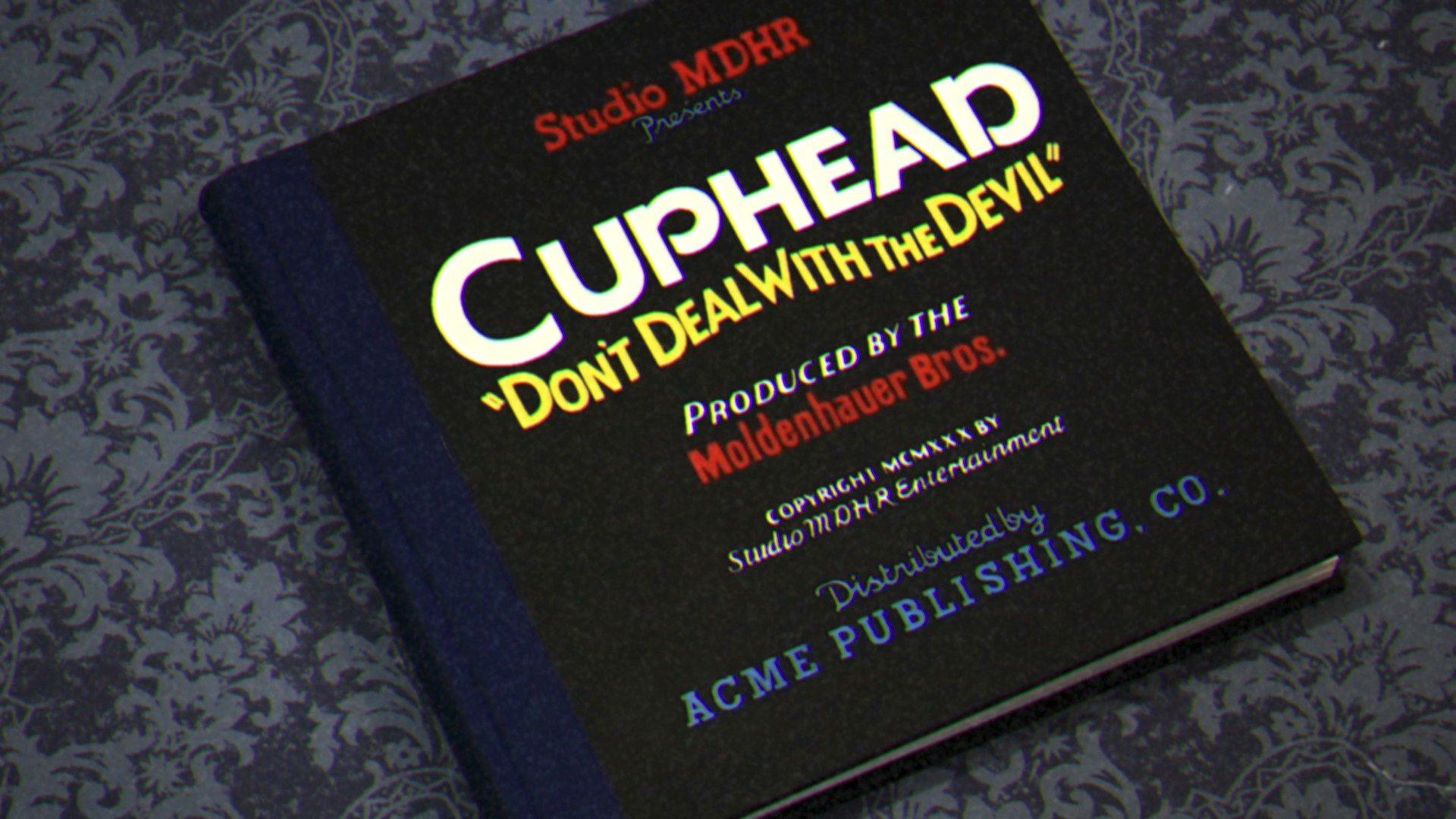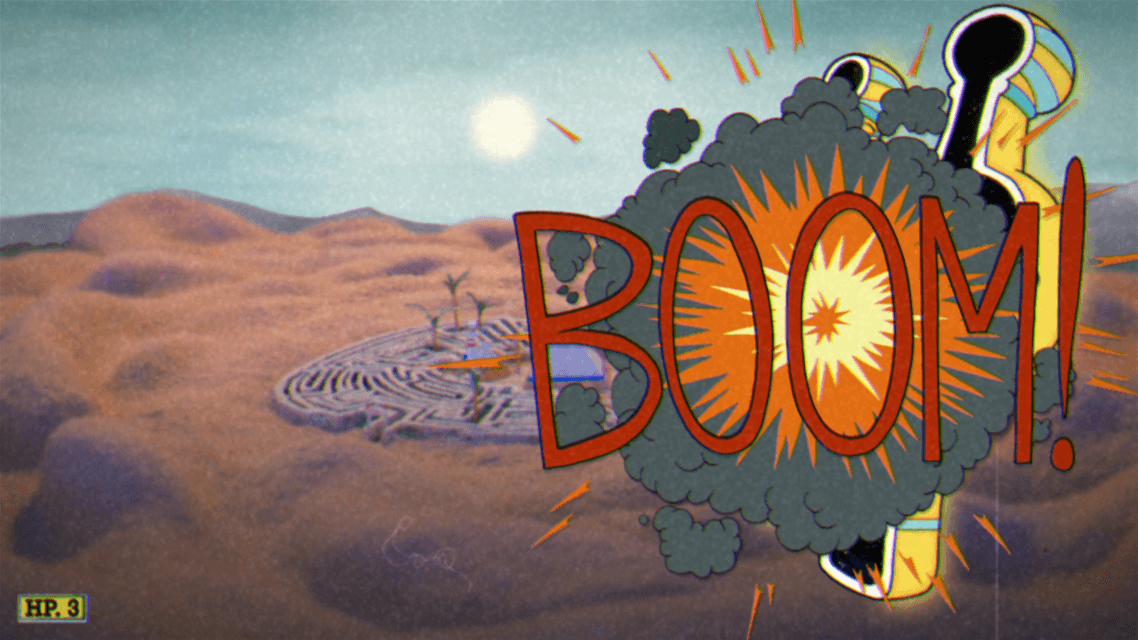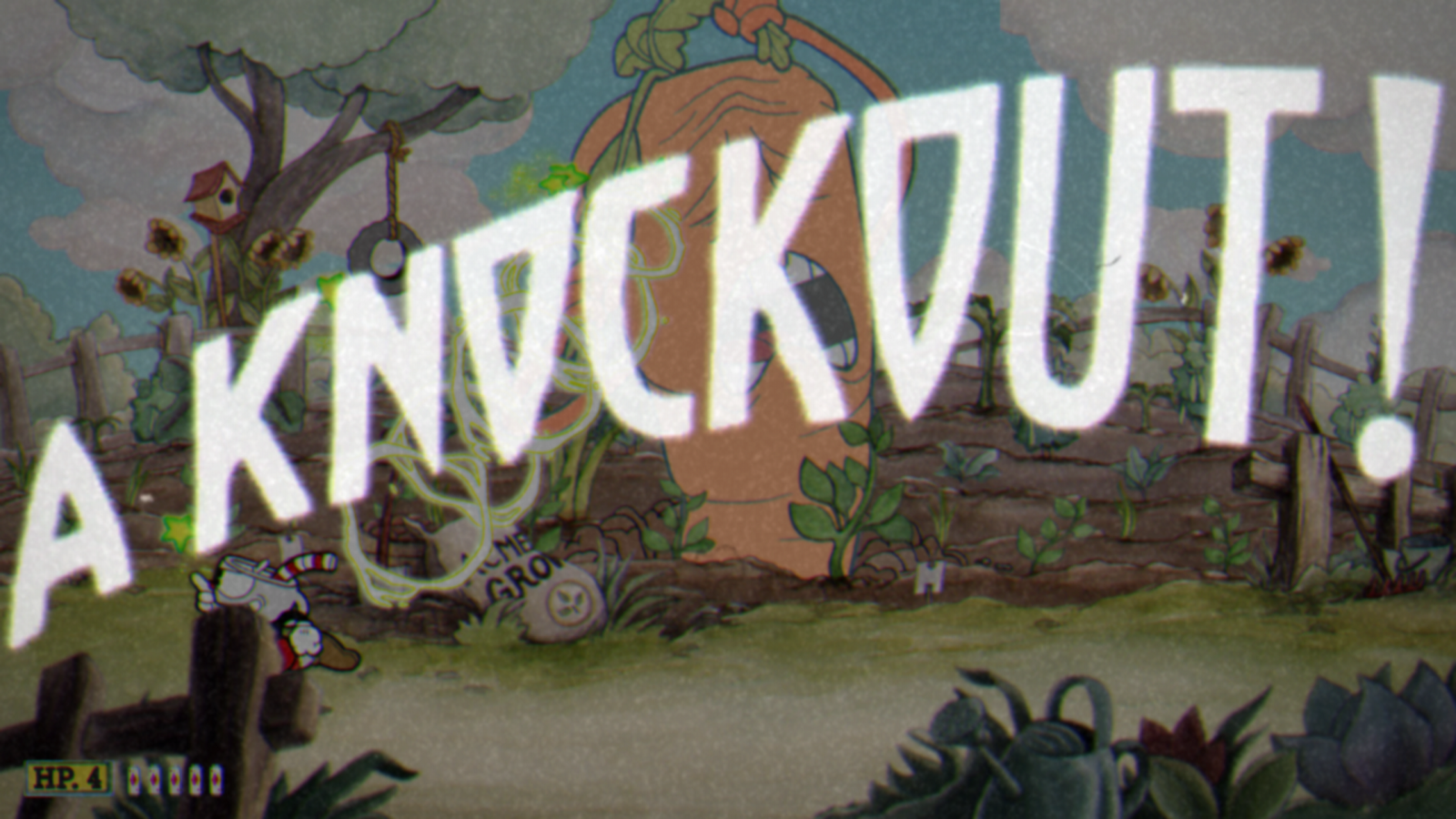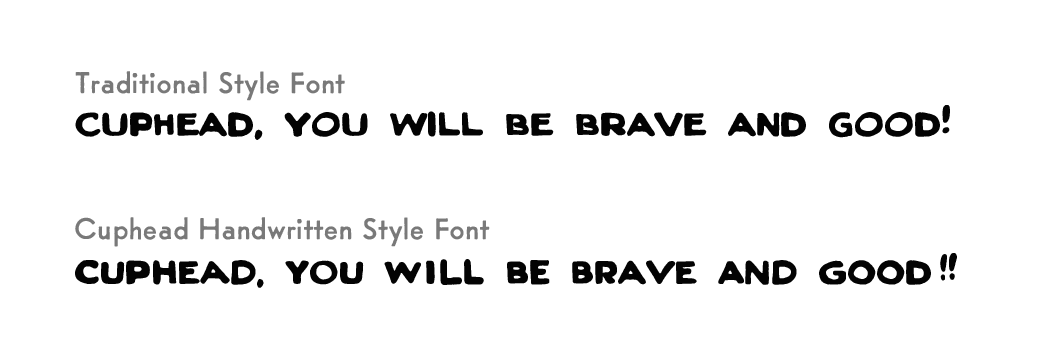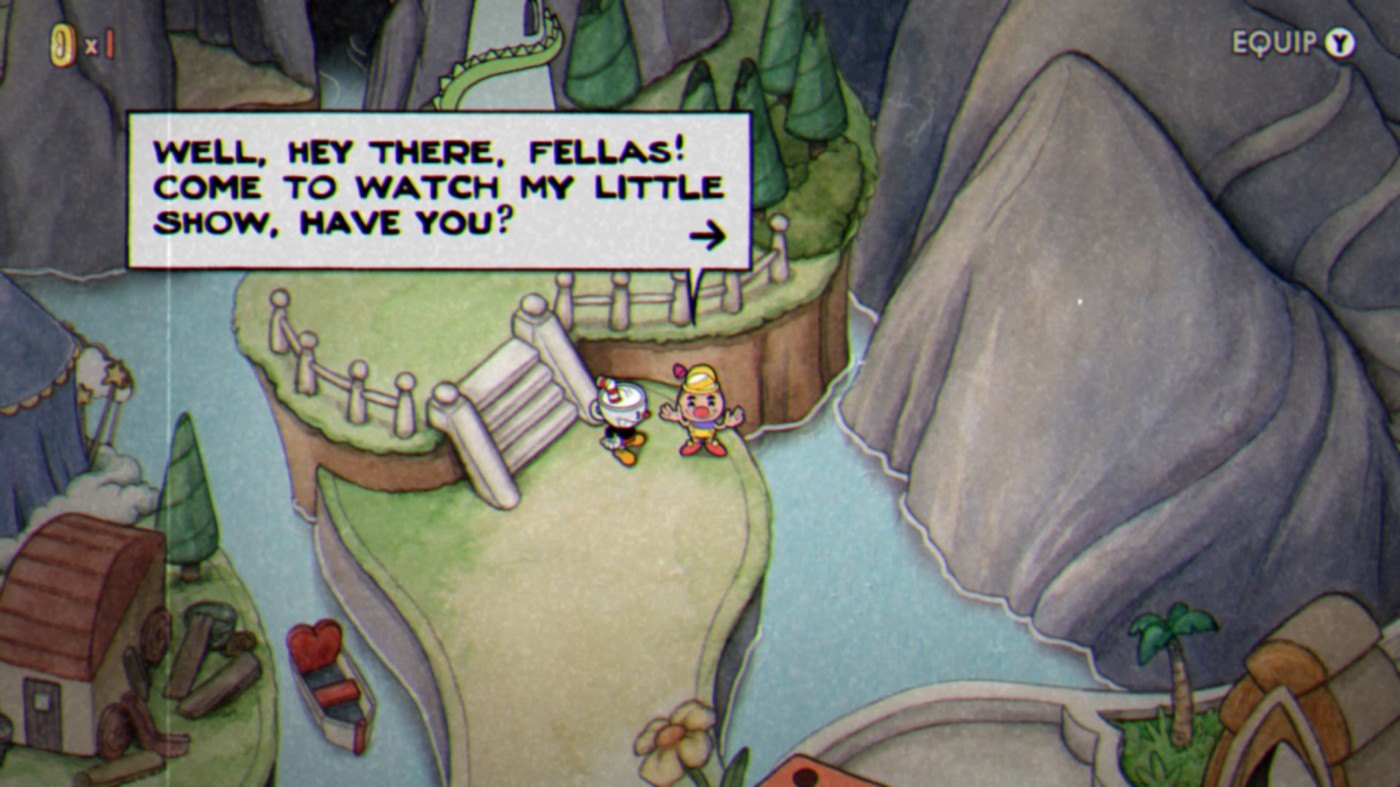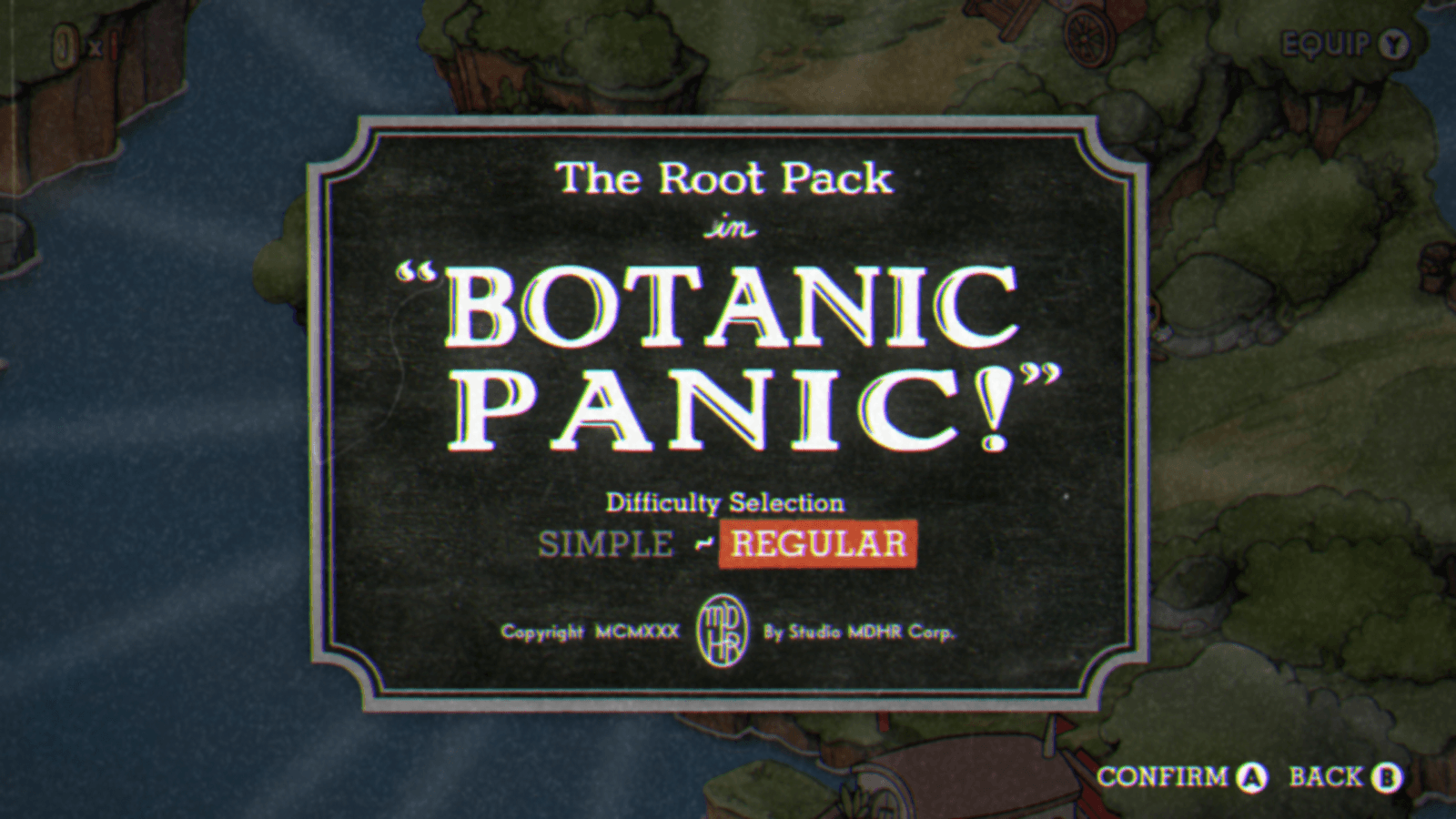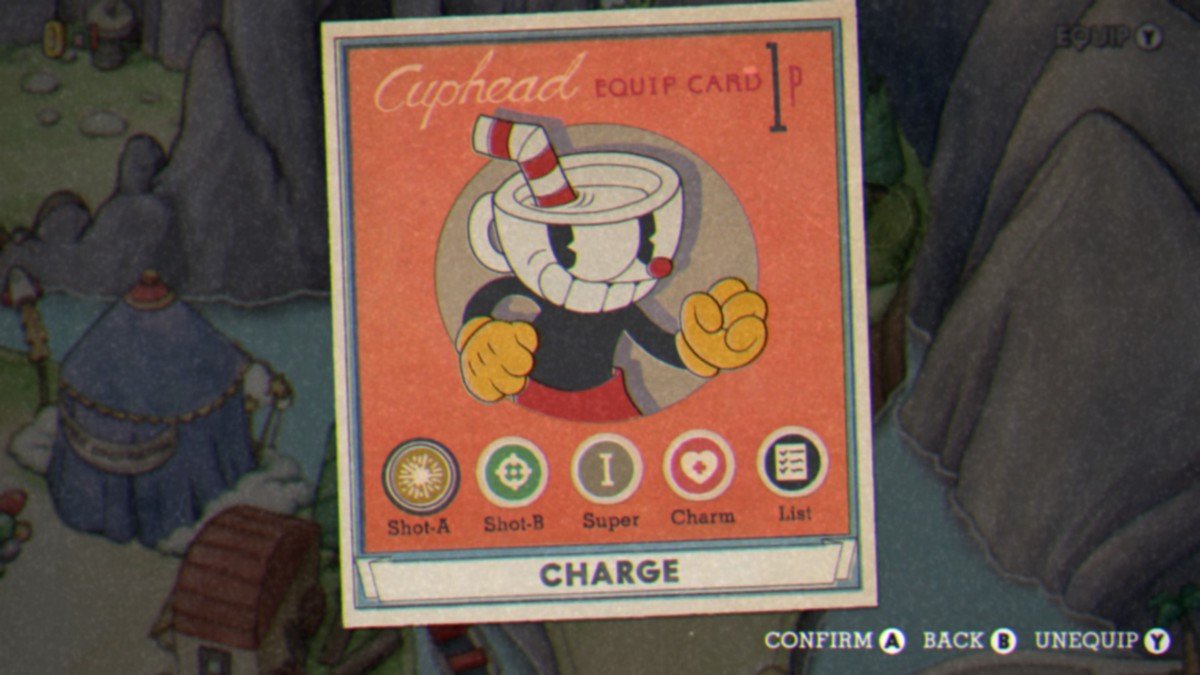
A tipografia em “Cuphead”
Jogo lançado no segundo semestre de 2017 impressiona pela direção de arte cuidadosa e trabalho tipográfico
Os fãs de jogos de plataforma ganharam um motivo para comemorar o mês de setembro de 2017: depois de ser adiado várias vezes, foi lançado “Cuphead” (disponível para PC e Xbox One), primeiro trabalho do estúdio MDHR. O jogo — que já era muito aguardado há anos — não decepcionou. Foi considerado um dos jogos do ano, sendo, por exemplo, premiado pelo The Game Awards como Melhor jogo independente de estréia; Melhor Jogo Independente e Melhor Direção de Arte.
Mas não só quem é fã de games de plataforma aproveitou “Cuphead”: o lançamento foi um presente também para fãs de desenhos animados. E, para o olhar mais atento, também para os interessado por tipografia. O jogo — que narra a saga dos irmãos Cuphead e Mugman enquanto tentam não perder suas almas para o diabo — é inspirado na estética das animações dos anos 1930 e 1940. Por isso, parte importante da sua direção de arte passa por aplicar essa estética ao desenho das letras que acompanham seus cenários e personagens.
[quoteesquerda]Quase tudo foi desenhado exclusivamente para “Cuphead”. Apenas uma fonte foi comprada externamente[/quoteesquerda]
“Cuphead” utiliza a tipografia como importante elemento narrativo (não apenas comunicativo) em momentos chave do jogo. Qualquer pessoa que tenha jogado “Cuphead” deve concordar: a aparição das frases “A KNOCKOUT!” ou “BRAVO!!!” preenchendo quase toda a tela nos finais de fase gera uma sensação de recompensa à altura da alta dificuldade de vencer cada etapa do jogo. A tipografia ainda ajuda a estabelecer o ambiente de cada fase: as batalhas com “chefões” são iniciadas com a frase “WALLOP!” escrita toda em letras maiúsculas, enquanto que as fases de plataforma (sem chefes) iniciam com “Run’n Gun!” escrita com maiúsculas e minúsculas e em tamanho menor na tela, de forma menos “urgente”. As letras ainda aparecem como elemento narrativo na forma de onomatopéias, no decorrer de algumas fases do jogo.
A preocupação do estúdio com esse elemento está não apenas no uso, mas também nos desenhos das letras. Quase tudo foi desenhado exclusivamente para “Cuphead”. Apenas uma fonte foi comprada externamente. A Silentina, baseada em intertítulos de filmes do cinema mudo. Para realização deste trabalho tipográfico fizeram parte da equipe do estúdio dois profissionais especializados: Warren Clark — responsável pelas peças de lettering — e Mark Simonson, que atuou como consultor em tipografia e também desenvolveu seis das fontes utilizadas.
[quotedireita]As fontes do jogo foram produzidas a partir de amostras escaneadas de tipografias da década de 1930 e tracejadas digitalmente[/quotedireita]
É importante esclarecer que tecnicamente lettering não é a mesma coisa que tipografia: o primeiro refere-se ao desenho de letras pensadas para uma composição específica; já a tipografia diz respeito à sistematização do caracteres desenhados, com o objetivo de serem aplicados a qualquer layout. Entretanto, convenciona-se abranger o lettering dentro do escopo do termo “tipografia”.
“Cuphead” se utiliza dos dois recursos. Por exemplo, o título da imagem acima — “A KNOCKOUT!” é um lettering — , onde cada caractere foi pensado especificamente para a composição deste título, no qual a palavra é composta por uma curva crescente da esquerda para a direita (note como as duas letras “K” são diferentes uma da outra nesse contexto). Já os balões de fala, os menus e outros textos de comunicação do jogo são compostos por fontes (caracteres sistematizados para serem capazes de escrever qualquer palavra).
Mas mesmo quando se utiliza de fontes, “Cuphead” tenta simular o estilo dos letterings dos anos 30. Isso acontece claramente nos balões de fala do jogo, onde para a fonte aplicada foram criados caracteres alternativos e o mecanismo de texto adaptado para que cada frase não repetisse as mesmas formas dentro de um balão. Na segunda amostra da imagem abaixo a letra “E” tem formas diferentes nas palavras “CUPHEAD” e “BE”. O mesmo vale para o “D” em “CUPHEAD” e “GOOD”. A fonte modificada conta com duas versões para todos os caracteres e alguns possuem até três (R, S, T, L, N, E, A, B, C, H, O). A Imagem 4 mostra as três as versões da letra “O” (nas palavras “COME”, “TO” e “SHOW”). “É sutil, mas faz toda a diferença”, afirma Chad Moldenhauer, um dos criadores e diretor de arte do jogo.
O motivo disso é, mais uma vez, o momento que inspira o jogo: nos anos 30 e 40 o uso de famílias tipográficas — com tipos de metal — era pouco prático e pouco versátil, por isso a comunicação visual da época se beneficiava muito do trabalho dos letristas, que facilitavam o desenho e uso de letras. Por isso, o caráter “imperfeito” dos desenhos feitos à mão é buscado em “Cuphead”. Inclusive, todo o jogo é desenhado à mão, não apenas as letras.
“Durante as pesquisas sobre a época, percebemos que hand lettering era a única possibilidade. Como nós queríamos que “Cuphead” fosse bem fiel aos anos 1930, o lettering teria um papel importante nisso”, explica Moldenhauer.
As fontes do jogo foram produzidas a partir de amostras escaneadas de tipografias da década de 1930 e tracejadas digitalmente. Sobre esse processo, fala ainda Mark Simonson:
[quotelaranja]“Você tem que entender as limitações da composição de tipos naquela época; como eles eram espacejados, todas as irregularidades no alinhamento e outros elementos que criam aquela aparência”[/quotelaranja]
Em “Cuphead”, as fontes apresentam seus detalhes “falhos” tanto do desenho propriamente dito das letras como em alguns outros aspectos técnicos. No desenho é mais fácil perceber, como no exemplo dos balões de fala, onde as letras são deliberadamente inconsistentes. Os letterings do jogo seguem a mesma linha. Não fazem questão de parecerem perfeitos. Note como a perna do “K” na Imagem 2 possui um relevo incomum no seu lado esquerdo.
Perguntado se “Cuphead” poderia definir um marco para a tipografia nos videogames, Chad afirma: “Isso é um pouco difícil de definir. Nós não conhecemos nenhum jogo que tenha um uso tão extensivo de hand lettering (ou mesmo scans de tipos de metal), então existe a possibilidade de que “Cuphead” seja o primeiro, mas não temos provas disso”.